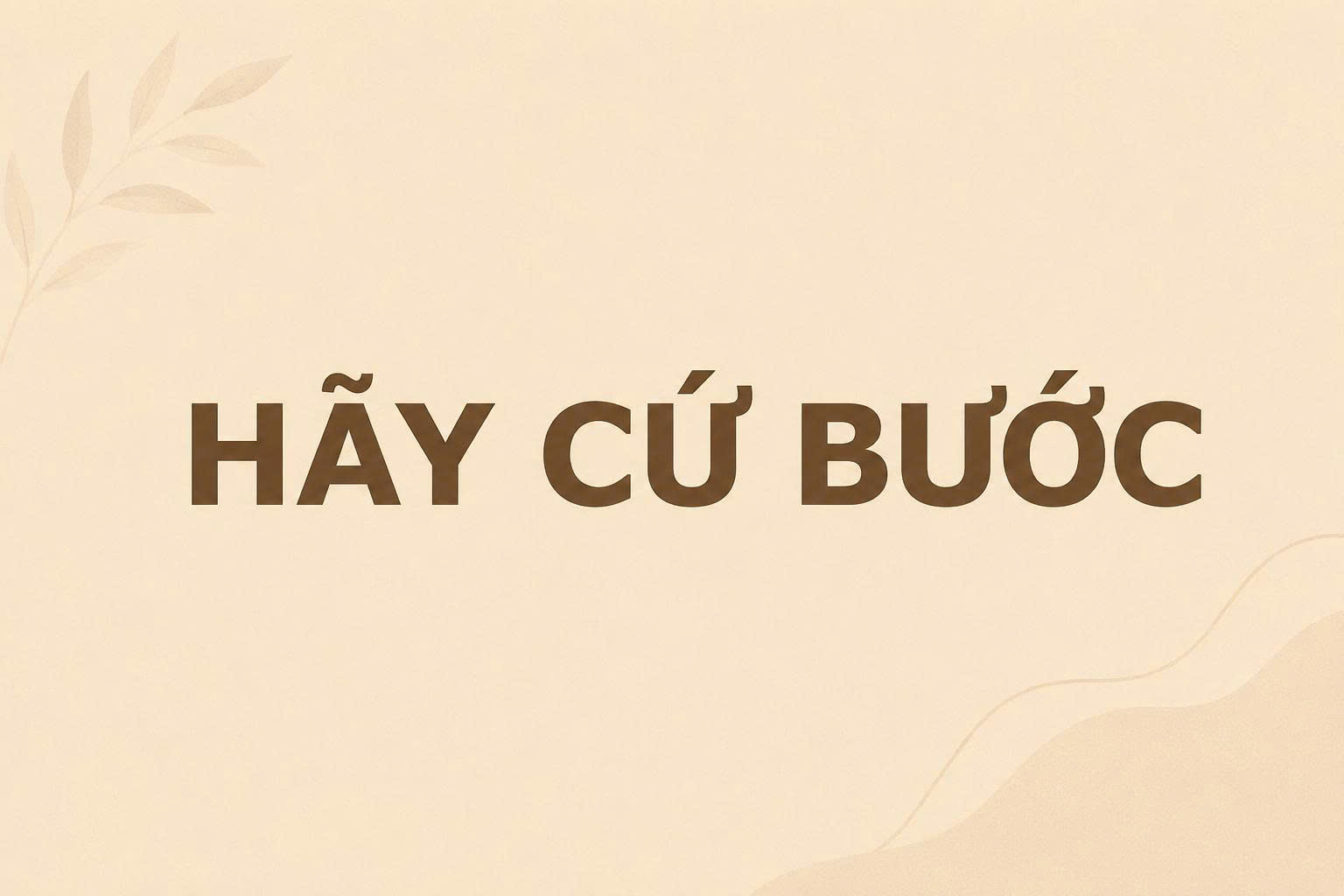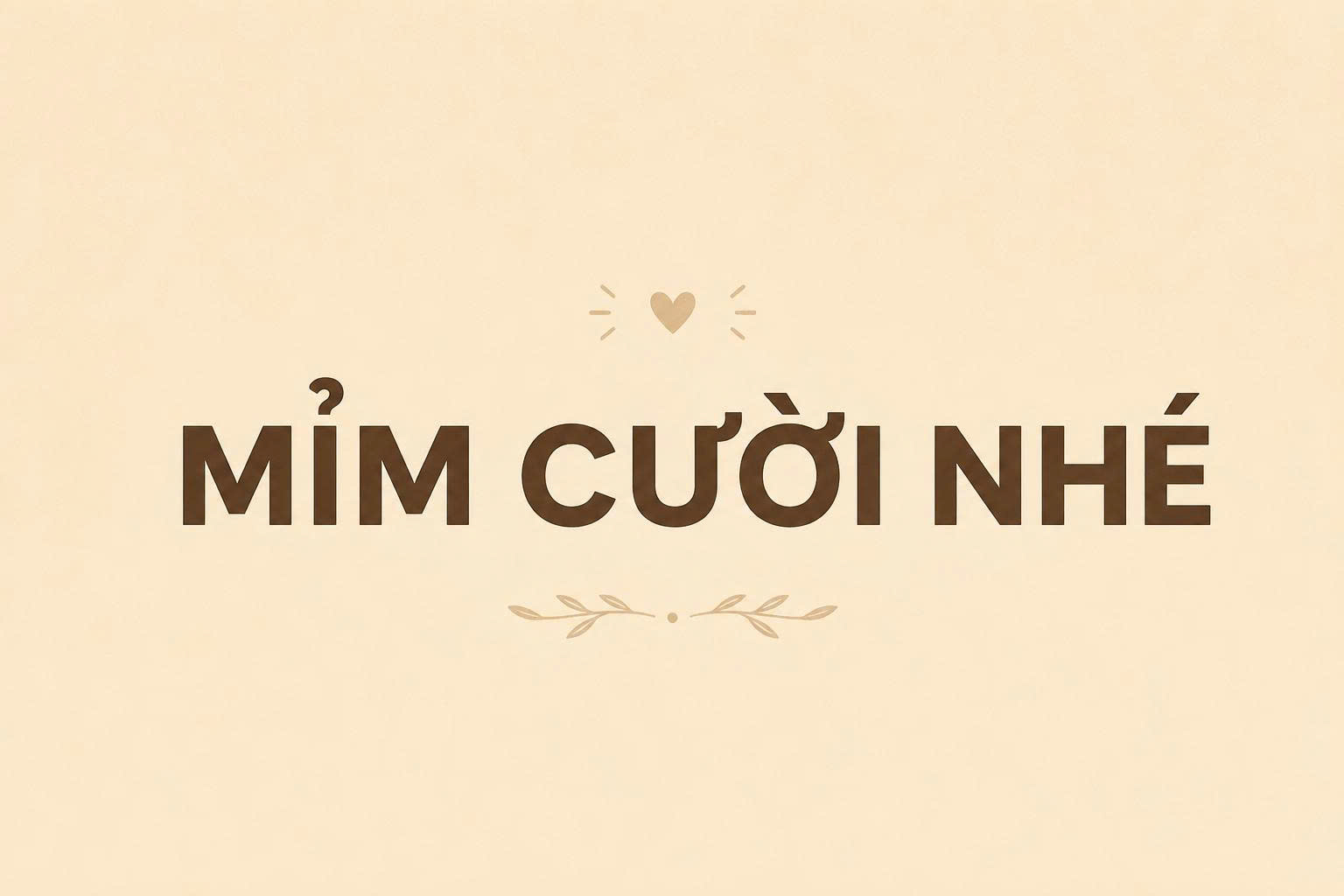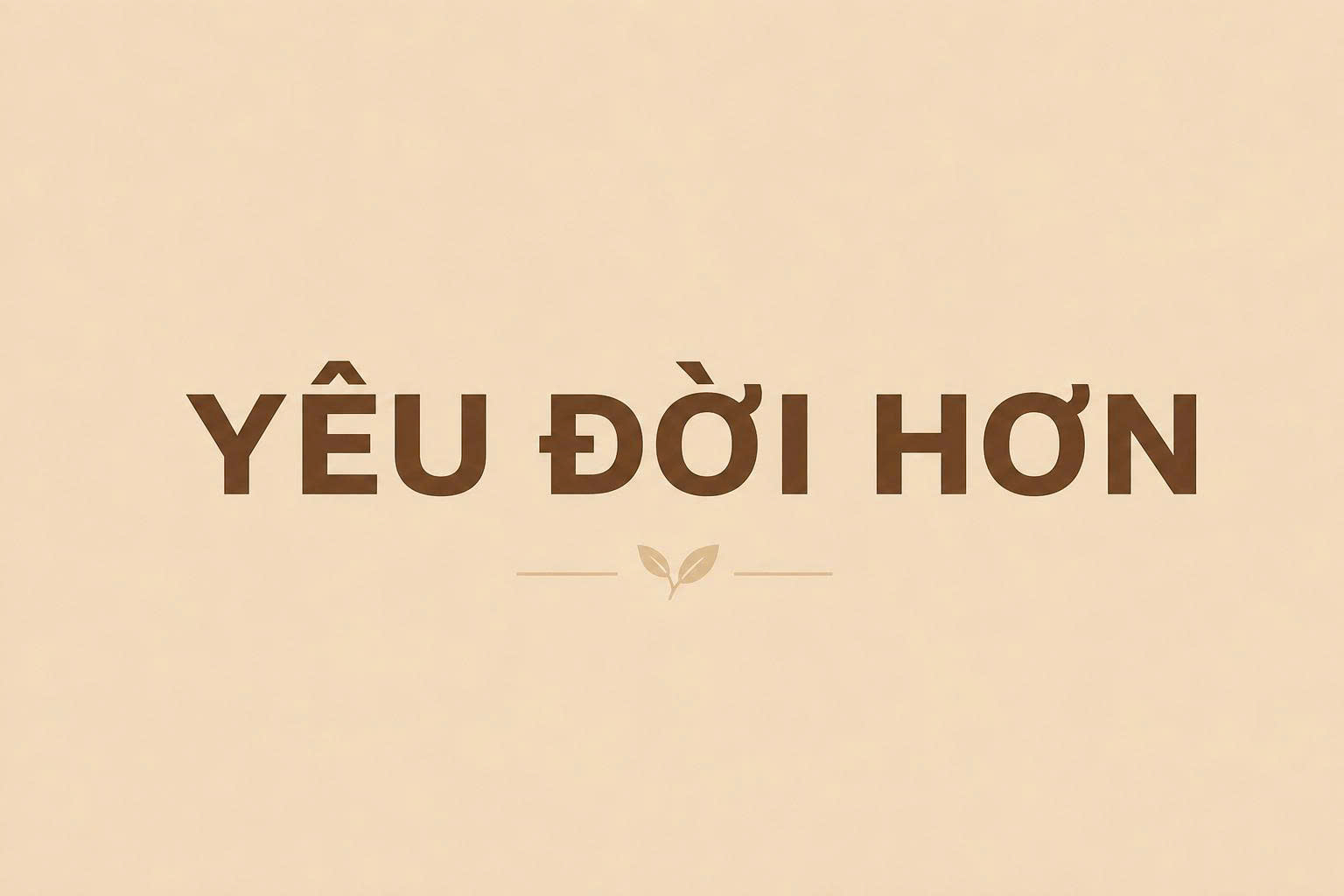
Font Verdana Việt hóa là phiên bản hỗ trợ đầy đủ bảng mã tiếng Việt của bộ phông chữ không chân (Sans-serif) kinh điển do Matthew Carter thiết kế cho tập đoàn Microsoft. Với ưu điểm nổi bật là cực kỳ dễ đọc ngay cả ở kích thước nhỏ hoặc trên màn hình độ phân giải thấp, Verdana đã trở thành tiêu chuẩn vàng trong thiết kế văn bản, website và đặc biệt là các thông tin chi tiết trên bao bì sản phẩm. Doozypack.vn cung cấp link tải font Verdana Việt hóa chuẩn, giúp bạn hoàn thiện các bản thiết kế chuyên nghiệp mà không lo lỗi font hay sai lệch dấu thanh.
Đặc điểm vượt trội của font Verdana trong thiết kế đồ họa
Verdana được tạo ra với mục tiêu tối ưu hóa trải nghiệm đọc. Điều này khiến nó khác biệt hoàn toàn so với các dòng font không chân khác như Arial hay Helvetica.
Độ dễ đọc tuyệt vời ở mọi kích thước
Verdana có phần “x-height” (chiều cao của các chữ cái thường như a, e, o) khá lớn so với tổng thể thân chữ. Đặc điểm này giúp mắt người dễ dàng phân biệt các mặt chữ ngay cả khi văn bản được in ở kích thước cực nhỏ, chẳng hạn như danh mục thành phần trên nhãn mỹ phẩm hay hướng dẫn sử dụng trên hộp thuốc.
Cấu trúc chữ rộng và khoảng cách thoáng
Các ký tự trong font Verdana có xu hướng được thiết kế rộng bản hơn, khoảng cách giữa các chữ cái (letter-spacing) cũng được tính toán để không dính vào nhau. Chính sự thông thoáng này giúp Verdana duy trì được độ sắc nét, không bị hiện tượng “bết mực” khi in ấn trên các chất liệu giấy có độ thấm hút cao như giấy Kraft hoặc giấy duplex.
03 Lý do nên sử dụng font Verdana Việt hóa cho in ấn bao bì?
Trong ngành in ấn và sản xuất bao bì tại Doozypack.vn, Verdana luôn nằm trong danh mục các font chữ “an toàn” nhất nhờ tính tương thích cực cao:
- Tính chuyên nghiệp: Verdana mang lại cảm giác chỉn chu, hiện đại và tin cậy cho thương hiệu.
- Hỗ trợ in ấn thông tin kỹ thuật: Các khối văn bản dài như bảng thành phần, địa chỉ sản xuất, mã vạch hoặc thông số kỹ thuật thường sử dụng Verdana để đảm bảo khách hàng có thể đọc rõ mọi thông tin pháp lý cần thiết.
- Không lỗi hiển thị: Việc sử dụng bản Việt hóa chuẩn đảm bảo các dấu thanh như “hỏi, ngã, nặng” không bị đè lên nét chữ hoặc quá nhỏ, giúp bản thiết kế đạt độ hoàn mỹ cao nhất.
| Biến thể Font | Đặc điểm | Ứng dụng đề xuất |
| Verdana Regular | Nét chuẩn, thanh lịch | Dùng cho nội dung mô tả, hướng dẫn sử dụng, thông tin thành phần. |
| Verdana Bold | Nét đậm, mạnh mẽ | Dùng cho tiêu đề phụ, tên sản phẩm hoặc các lưu ý quan trọng cần nhấn mạnh. |
| Verdana Italic | Nét nghiêng, tinh tế | Dùng cho các ghi chú, tên khoa học hoặc trích dẫn ngắn trong bao bì. |
Gợi ý lựa chọn: Đối với các bản in trên hộp giấy kích thước nhỏ, bạn nên ưu tiên dùng Verdana Regular ở size chữ tối thiểu 6pt để đảm bảo nội dung sắc nét. Hạn chế dùng Bold cho các dòng chữ quá nhỏ vì mực in có thể làm dính các nét chữ vào nhau.
03 Lưu ý kỹ thuật khi dàn trang nội dung in bằng font Verdana
Khi sử dụng font Verdana cho các thiết kế bao bì thực tế tại Doozypack.vn, bạn cần nắm rõ một số quy tắc sau để tránh sai sót khi thành phẩm:
- Kích thước chữ tối thiểu: Trên các loại giấy mịn như Couche hay Ivory, Verdana vẫn đọc tốt ở mức 5pt – 5.5pt. Tuy nhiên, nếu in trên giấy Carton sóng hoặc giấy Kraft, hãy giữ kích thước chữ từ 7pt trở lên để tránh bị mất nét do bề mặt giấy không phẳng.
- Khoảng cách dòng (Leading): Với đặc điểm chữ rộng bản, bạn nên đặt khoảng cách dòng lớn hơn mặc định (khoảng 1.2 – 1.4 lần size chữ) để khối văn bản trông thoáng đãng và dễ theo dõi hơn.
- Hệ màu in ấn: Khi in các đoạn văn bản nhỏ bằng font Verdana, hãy đảm bảo chữ được đặt ở hệ màu K=100 (đen nguyên chất) thay vì màu đen tổng hợp (C,M,Y,K) để tránh hiện tượng chữ bị nhòe màu (lé màu) khi in chồng lấp các bản kẽm.